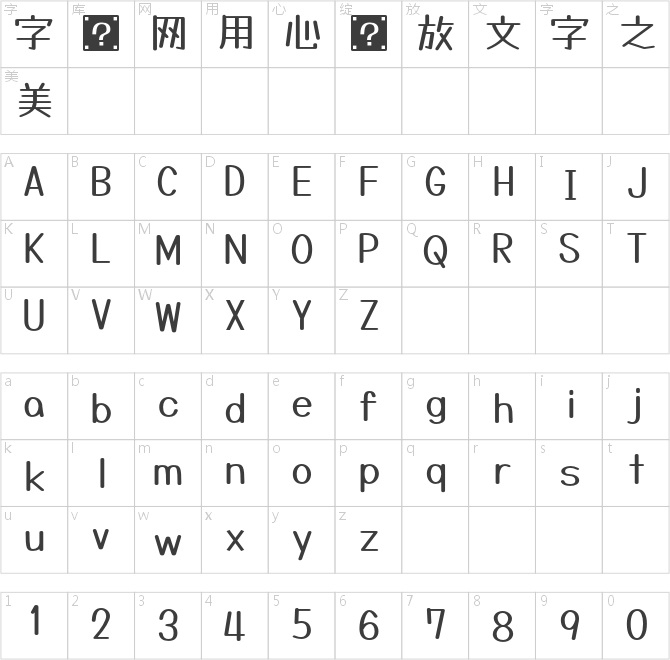
字体名称: Tanugo手
字体类型: 日文字体
Tanugo手写字体
Tanugo手写字体介绍
Tanugo手写字体字体Tanugo字库是一款让人赏心悦目、百看不厌的日文字体,适合各类广告和产品包装设计应用,字体大小3.53MB,格式为otf字体,上传用户是锦程正阳,作者/版权方为たぬきフォント